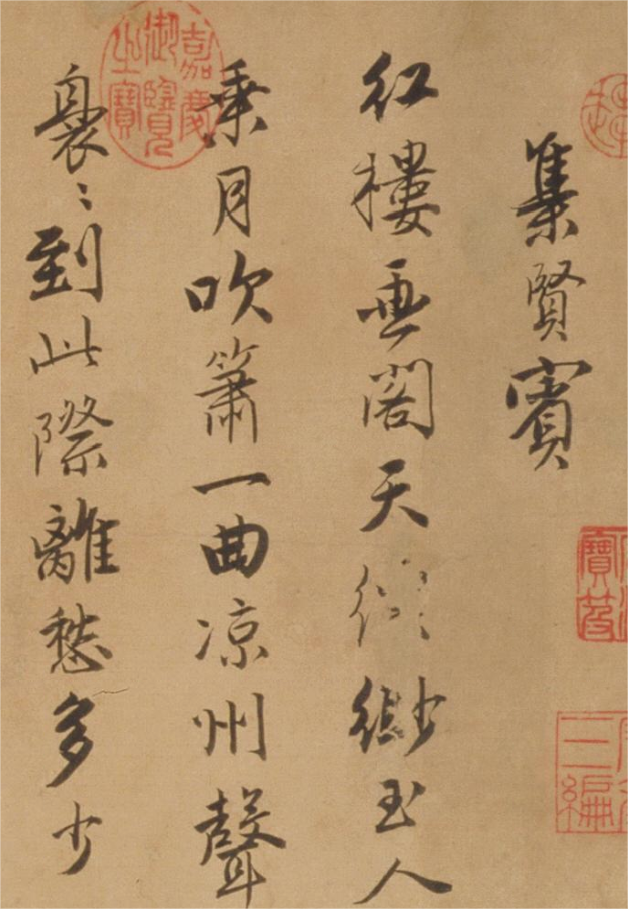
字体全名: 汉标唐寅行书自书词卷
字体简介: 下载须知:本字库非标准GB2312字库。本字库只包含了唐寅自书词卷真迹上的“1506个字”。所在藏馆:北京故宫。此为唐寅所作词并自书,分《集贤宾》、《锦衣公子》、《山坡羊》三组曲牌,共24首。唐寅博学多能,吟诗作曲,能书善画。他的传世绘画较多,书法甚少。其书以行楷见长,学赵孟頫并参以李北海笔意,笔画婉转流畅,风格俊秀潇洒。此书结构严谨,圆转遒丽,丰润优雅,形成了劲骨于内、美形于外、缜密流便的独特风格,词、书并美,堪称珠联璧合,从中可欣赏到往昔“江南第一风流才子”的儒雅韵致及其纯熟的书法功力。